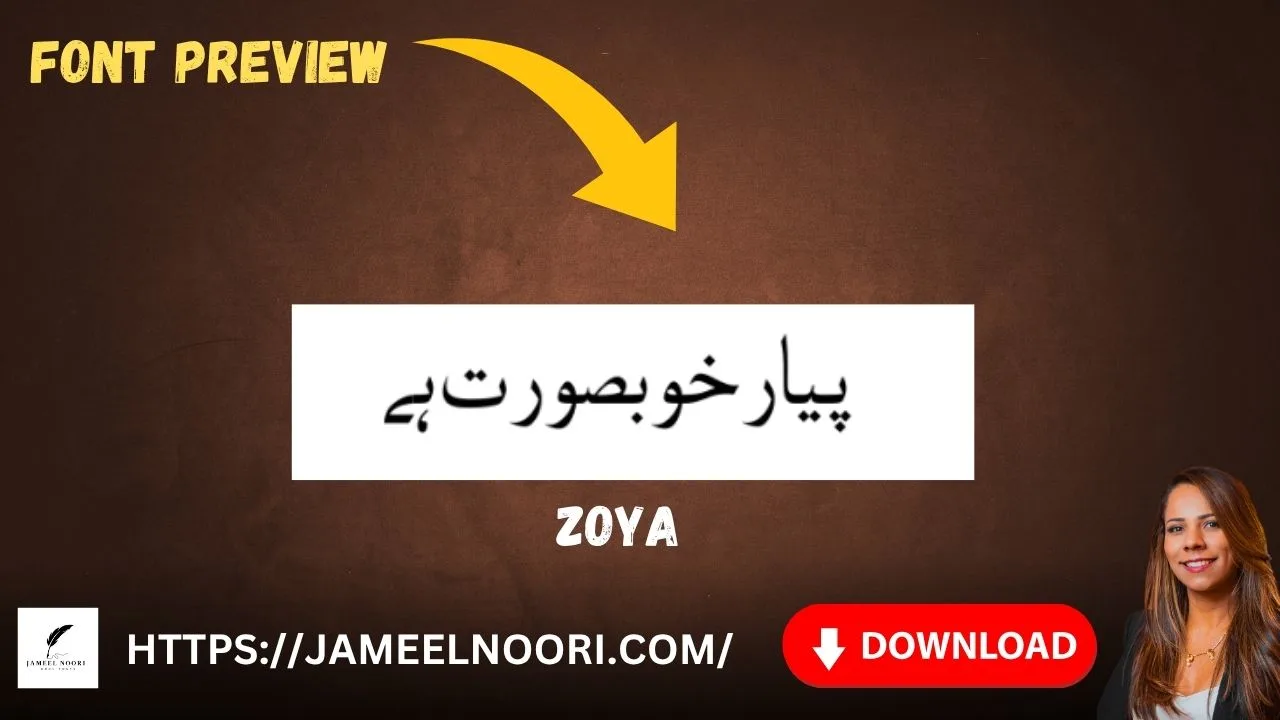
Introduction to Zoya Urdu Font
Download Urdu Font Zoya ek stylish aur elegant Urdu TrueType Font hai jo specially Urdu writing aur designing ke liye banaya gaya hai. Ye font high readability aur smooth curve design ke sath aata hai jo har Urdu project me professional look deta hai.
Features & Technical Details of Download Urdu Font Zoya
Download Urdu Font Zoya Pakistan ke Urdu font lovers ke liye ek perfect Urdu font hai. Ye font lightweight, stylish aur readable dono hai. Neeche iske features aur technical specifications di gayi hain:
Design StyleNaskh-Based Elegant Font
Key Highlights:
• Beautiful Urdu Typography: Perfect for Urdu writing aur calligraphy.
• Smooth Design: Har letter balanced aur readable.
• Stylish Look: Urdu quotes, posters aur titles ke liye ideal font.
Best Uses of Download Urdu Font Zoya Stylish Font
Download Urdu Font Zoya ko aap multiple purposes ke liye use kar sakte hain:
• Urdu quotes aur poetry design ke liye
• YouTube thumbnails aur posters ke liye
• Urdu blog writing aur headings ke liye
• Social media post designs ke liye
💡 Ye font readability aur beauty ka best combination provide karta hai.